フォント業界の未来について本気出して考えてみた「ai(人工知能)が作るフォントの世界」
フォント業界のこれから先を考える上で「AI」がキーワードの1つになりそうな気がする、これは別に勘でもなんでもなく、確かな裏付けがあるのだ。
「AI」と書いたが、私が指す「AI」とはフォント業界と密接に繋がる多くの仕事をこなす上での相棒的存在「Adobe Illustrator」の略ではなく、ましてやアメリカ合衆国生まれ、鹿児島県育ちの「Story」をヒットさせた歌手なんてもんでなく、まして辛い時にお世話になってますがチョコラBBシリーズで知られる医薬品メーカーでもない。つまり「artificial intelligence」、いわゆる人工知能を指している。
ディープラーニング(深層学習)を導入した「AI」が囲碁などのトップ棋士やポーカーの世界トップクラスのプレイヤーを破るなど、その革新的な技術の進化が話題となる一方、「AI」の進化により、職業が奪われるのではないかなどといった不安な声も挙がっている昨今、少し古い情報となるが、週刊ダイヤモンドの2015年8月月22号にて「機械が奪う職業・仕事ランキング(米国)50」も発表されているのだ。
これからの子供は将来、競争社会の中でAIとも戦わなくてはいけないかもしれないと思うと少し焦る。
上位陣を挙げてみると小売店販売員、会計士、一番事務員、セールスマン、一般秘書、飲食カウンター接客係、商店レジ打ち係や切符販売員、箱詰め積み降ろしなどの作業員、帳簿係などの金融取引記録保全員、大型トラック・ローリー車の運転手などがランクインし、上位陣を含め、しっかりと二度見したが、職業ランキング50位に書体設計士、フォントデザイナーはランクインしていなかった。
「ニッチ過ぎるからさ…」という意見はひとまず置いておいて、フォント業界にとっても「AI」は対岸の火事では断じてない。それを強く裏付ける証拠として2017年5月11日に開催されたモリサワ主催によるセミナー「グローバル・タイプデザイン」にあった。
モリサワが主催する書体デザインのアワード「タイプデザインコンペティション 2016」表彰式と同時開催で行われたこのセミナーでは、台湾の「Arphic Technology co., LTD」、韓国の「Sandoll Communications Inc.,」、アメリカの「Type Network」、中国の「北京漢儀科印信息技術有限公司」といった書体メーカーが集い、各国の書体デザインの特長や各社の最新事情について講演された。
講演の最後にモリサワは「AI」による日本語フォント設計の開発を検討している事を発表していた。時間としては少なめで「AI」が話題となる昨今におけるリップサービス、余興的な意味もあったのかもしれないけれど、日本語フォント設計の作業効率を推し進める上で、また、異なる書体のストロークを掛け合わせて新書体を設計するなどといった事を「AI」に行わせることを検討しているといった内容で、奮闘していた通訳サンには悪いが、グダグダな状態だったセミナーの中で、唯一興味深い内容に思えた。
平仮名、片仮名、漢字、アルファベット、数字までパッケージング化された日本語フォントの設計はとにかく作業が大変だ。例に挙げるとOpenTypeフォントに「Adobe-Japan1-3」などと書かれているのを見たことがお有りだろうか。
「Adobe-Japan1」とは、アドビシステムズ社が日本語DTP用に開発した文字集合規格で、2013年現在Adobe-Japan1-0から1-6までの7種類の定義が済んでいる。この数字は末尾の数字が大きくなればなるほど、文字数は多くなる。
現在、最も多い「Adobe-Japan1-6」では23,058文字、漢字は14,663文字という途方もない文字数を収録しているのだ。23,058文字というその数字が指し示す通り、1書体設計するだけで膨大な作業量となる。
普段から「日本語書体って高すぎる!」と怒りにプルプルと震えている方は、その昔、人気漫画ジョジョの奇妙な冒険第6部のラスボスでプッチ神父による「落ち着け………… 心を平静にして考えるんだ…こんな時どうするか……2… 3 5… 7…落ち着くんだ…『素数』を数えて落ち着くんだ…『素数』は1と自分の数でしか割ることのできない孤独な数字……わたしに勇気を与えてくれる」という台詞があったが、それに倣って「落ち着け………… 怒りを鎮めて考えるんだ…日本フォントが高い時どうするか……23,058文字…23,058文字…落ち着くんだ…文字数を知って落ち着くんだ…23,058文字あれば……きっと文字化けはない、印刷事故の無い世界を与えてくれる」と落ち着くのが良いかもしれない。ちなみに漫画の吹き出しに文字を入れる際は「アンチック体」という書体を使用しよう。「アンチック体」は、ゴシック体漢字にあわせた太かなとして誕生したと言われ、マンガの吹き出しの他、辞書の見出しや絵本などに多く使用されている。
「23,058文字」という文字数を以てしても、ドラゴンボールのフリーザが言い放った「私の戦闘力は53万です」という1桁違う数字に比べたら、「まだまだだね」とテニスの王子様の越前リョーマ的なカウンター的台詞を以て「企業努力でどうにかしろ!」とお怒りの方は、一刻も早いフォント設計の「AI」を願おう。ちなみにこうした漫画の吹き出しに文字を入れる際は「アンチック体」という書体を…、という話は、さっきもう書いていたわけだが、原稿の文字数を稼ぐためにわざともう一度書いたわけでない、多分。
ちなみにモリサワがフォント設計のオートメーション化を実現したとして、浪速の商人的思考を持つモリサワの事だ。適切なタイミングで公にするのだろうか? 疲れを知らず、何時間でも作業が可能な「AI」によるフォント設計により人件費が浮いてもモリサワパスポートの値段を安くすることなどない気がする。
外部発注やコンペ受賞作品ではデザイナーがその他の書体に関しては別だが元々、モリサワはリリースするフォント設計者・フォントデザイナーについて公にしていない。名探偵コナンを愛読している私が公にできないその理由を推理してみたところ、実は既にモリサワのフォントデザインの一部を「AI」が設計しているからだという結論に至ったのだった。
そんな未来を生きているかもしれないモリサワは、現在「タイプデザインコンペティション 2019 (Morisawa Type Design Competition 2019)」でバリアブルフォント(Variable Font)の技術を安値で買い叩こうとするハゲタカでもある。バリアブルフォントとは1つのファイルでありながら複数のフォントのように動作するフォントで、ファイルサイズを拡大することなくウェイトや幅、傾斜などの属性を変更することができるデジタルフォントの新しい技術のこと。
これまで「タイプデザインコンペティション」の賞の1つである「明石賞」は、前回までは製品化する書体を募集していたが、新たに毎回異なるテーマに沿った書体を募集するカテゴリに変貌を遂げた。そして、現在、フォント業界で話題になっている「バリアブルフォント」を評価すると銘打ち、入賞賞金は50万円で最大3点までの受賞が用意されている。合計150万円で、世界各地のデザイナーやエンジニアが用意したバリアブルフォントの技術やアイデアを労せずに手に入れられると思えば決して高くない、さすがは浪速の書体商人モリサワである。
これからのフォント業界がどうなるかはさておき、2017年モリサワは、私も劇場で2回、家で1回観た大ヒット映画「君の名は。」のタイトルとしてお馴染みの「A1明朝」に続く新書体「A1ゴシック」という書体を発売している。
A1ゴシック
「A1ゴシック」は、A1明朝の基本となる骨格を参照して作成されたオールドスタイルのゴシック体ファミリーで、線画の交差部分の墨だまり表現や、エレメントの端々に僅かな角丸処理を加えることで温もりのあるデザインに仕上げている。
あれ「A1ゴシック」って…、
A1ゴシック…、
A1…、
AI…、
AIゴシック…。
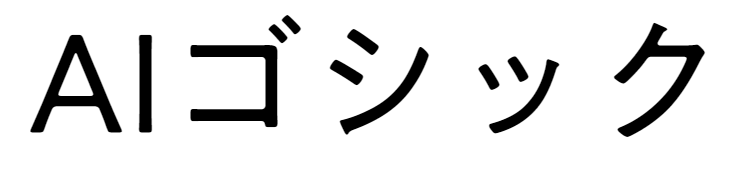
飛躍してしまった、このフォントとAIに関する話が本当かどうか信じるか信じないかはあなた次第となりますが、あら? 誰かがノックしているようなのでちょっと出てきますね、ではまた。